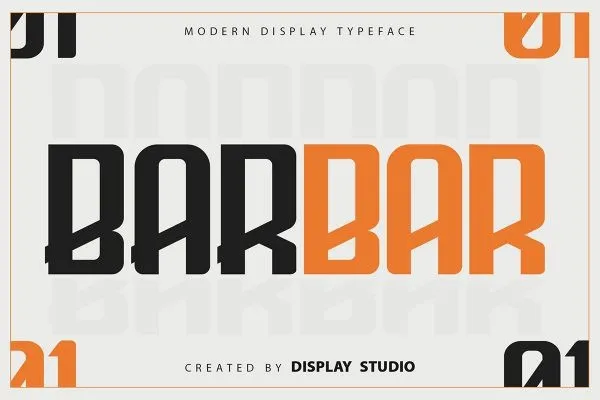
Esta fonte ‘Barbar’ é uma atração perfeita para quem busca algo notável e marcante. Desenvolvida pela Display Studio, esta fonte display apresenta um estilo agressivo e elegante, que se destaca com sua precisão e forte personalidade. Ideal para uso em logotipos de marcas, cartões de convite ou até mesmo em projetos menos formais, a Barbar atinge perfeitamente o que procuramos: uma identificação forte e um toque moderno. Com a funcionalidade multilíngue e as variedades do estilo, a Barbar adiciona um toque extra ao seu trabalho. Permite não apenas transmitir uma mensagem clara e assertiva através de seus logotipos, cartões de convite ou mensagens publicitárias, mas também expande o universo do design gráfico com sua versatilidade e sofisticação. É a escolha perfeita para quem busca um visual criativo e moderno que se destaca em qualquer aplicação onde seja usada.